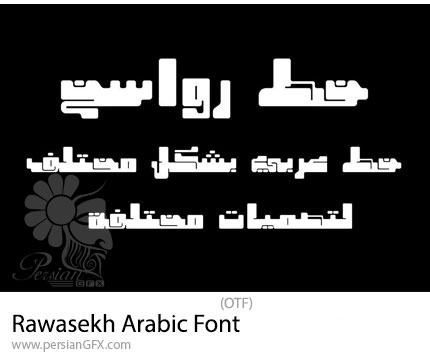
در این بخش شاهد فونت عربی به نام رواسخ می باشید که با فرمت OTF بر روی سایت برای دانلود قرار گرفته است. فونت Rawasekh Arabic یکی از فونتهای مدرن و زیبای عربی است که برای طراحی متون عربی با ظاهر شیک و حرفهای مورد استفاده قرار میگیرد.
1. معرفی فونت:
- این فونت یک فونت نمایشی (Display Font) با سبک معاصر است که برای زبان عربی طراحی شده، اما قابلیت پشتیبانی از متون فارسی نیز در برخی نسخههای آن وجود دارد. این فونت با هدف ایجاد تعادل میان اصالت خوشنویسی عربی و زیباییهای طراحی مدرن ساخته شده است.
2. ویژگیهای ظاهری:
- حروف با ضخامت مناسب: فونت Rawasekh دارای خطوط صاف، قوی و ضخیم است که جلوهای رسمی و قابلاعتماد به متن میبخشد.
- فرمهای هندسی: طراحی حروف با فرمهای هندسی و ساختاری دقیق انجام شده که باعث خوانایی بالا در اندازههای بزرگ میشود.
- استایل نوین: این فونت نسبت به فونتهای سنتی عربی ظاهر مدرنتری دارد و برای استفاده در عناوین، پوسترها و طراحیهای گرافیکی مناسب است.
3. کاربردها:
- طراحی جلد کتابها و مجلات عربی و فارسی
- استفاده در لوگوها و برندینگ با محتوای عربی
- تایپوگرافی پوسترهای تبلیغاتی و فرهنگی
- پروژههای دیجیتال مانند اپلیکیشنها و وبسایتهای عربزبان
4. زبانهای پشتیبانیشده:
- زبان عربی
- در برخی نسخهها، زبان فارسی و اردو نیز پشتیبانی میشود، اما بسته به نسخه ممکن است نیاز به بررسی دقیقتر باشد.